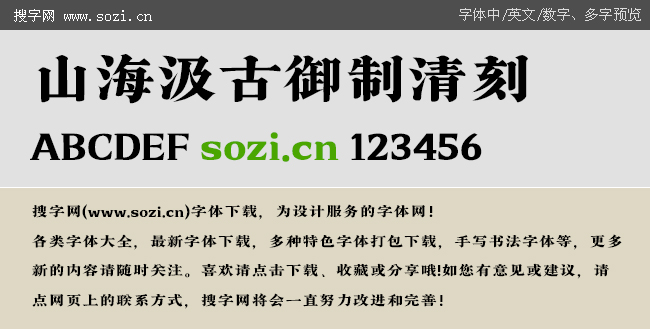
山海汲古御制清刻
搜字網(wǎng)提供一款山海汲古御制清刻中文字體下載,山海汲古御制清刻是一款雕版風(fēng)格的粗宋體字體。山海汲古御制清刻粗壯醒目,字形端莊大氣,視覺效果非常不錯(cuò)。適合標(biāo)題設(shè)計(jì)、海報(bào)設(shè)計(jì)、廣告設(shè)計(jì)等應(yīng)用。